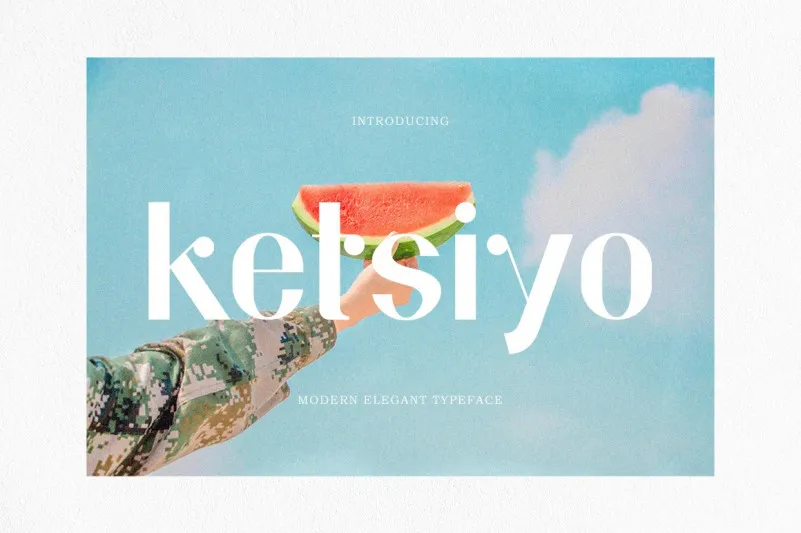
A Ketsiyo Font é uma elegante tipografia com cobertura extensa que abrange desde a design editorial até a web design. Esta fonte foi projetada e compartilhada pela Salamah Studio, e apesar de ser simples em aparência, possui um forte efeito visual. Ela irá tornar sua criação ainda mais atrativa comparada com qualquer outra opção disponível no mercado. A Ketsiyo é perfeita para designers que valorizam uma fonte moderna, minimalista e poderosa, capaz de destacar seus projetos em design editorial e web design sem precisar de muitas intervenções adicionais. Como se trata de uma fonte de tipo sólido, ela será um ótimo complemento para qualquer projeto gráfico, tornando suas criações mais atraentes e sofisticadas.